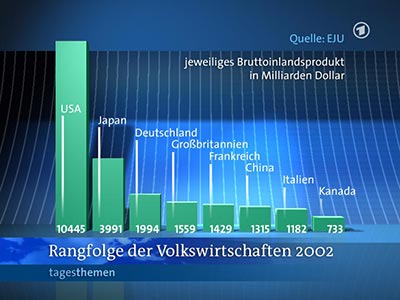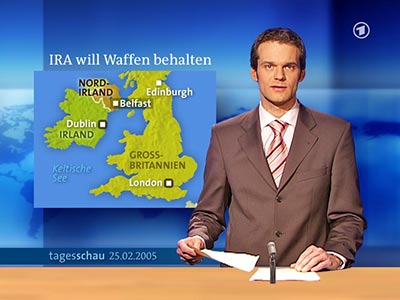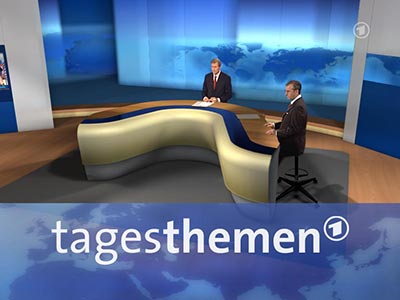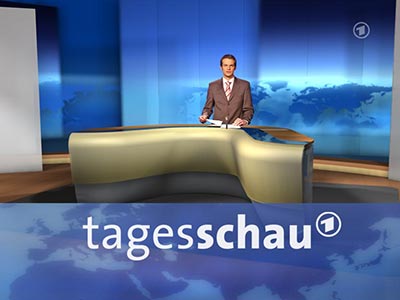
Aus der ARD-Design-HexenkücheFontShop-Beirat und Kreativdirektor der ARD-Design-Agentur DMC Markus
Hanzer hat uns Bilder aus der Entwurfsphase des
Tagesschau/Tagesthemen-Redesigns geschickt. Hanzer kämpft seit 4 Jahren
für die Erneuerung der Nachrichtensendungen. »Du kannst Dir nicht
vorstellen, wie unglaublich mühsam dieser Prozess ist« schrieb er uns
heute. Seiner Mail lagen 4 Abbildungen bei, die im Februar 2005 den neuen Weg
wiesen
...
![]() Markus Hanzer über die Rolle des Designs in News-Sendungen:
»Nachrichtenprogramme leben vom Vertrauen, von der Glaubwürdigkeit und
von der Aufmerksamkeit die ihnen geschenkt wird. Im Vordergrund steht deshalb
der ungetrübte Blick auf die Ereignisse des Tages. Dort jedoch, wo Fakten
sich nicht unmittelbar im Bild festhalten lassen, muss Design diese sichtbar
machen.«
![]() Tagesschau-Intro in der Entwurfsphase: ruhiger Hintergrund, Modell eines Nachrichtentischs, stehende Moderation Hanzer über die Bedeutung der Schrift für das Corporate Design eines TV-Senders: »Typografie ist auch im Bereich bewegter Bilder ein leistungsfähiges Instrument, um die Marke des Absenders sichtbar zu machen und über die vermittelten Inhalte hinaus von der eigenen Grundhaltung zu erzählen.« ![]() Tagesthemen-Intro in der Entwurfsphase: Doppelmoderation, Stehhilfe, U-förmiger Nachrichtentisch Hanzer über die Vorzüge der Schriftsippe Thesis: »Mit Hilfe der Thesis und der auf dem gleichen Formenkanon aufbauenden TheAntiqua B von Lucas de Groot steht ARD aktuell eine Schriftfamilie zur Verfügung, die allen Anforderungen einer modernen Berichterstattung gerecht wird.« ![]() Schwebende Hintergrundgrafik (Schrift TheSans), weiße Schlagzeile (TheAntiqua), vertrautes ARD-Blau Hanzer über die verbesserte typografische Darstellung: »Aktuelle Produktions- und Übertragungstechnik sowie eine deutliche Verbesserung bei der Bildqualität der Endgeräte erlauben heute einen differenzierten Umgang mit Schrift auf dem Bildschirm.« ![]() Aufwändige Säulengrafik wie in einer Tageszeitung: TheAntiqua-Headline, TheSans-Beschriftung, Proportionalziffern Das von Markus Hanzer mit der Agentur DMC für ARD aktuell entwickelte Design knüpft bewusst wieder an die hoch entwickelte Tradition der Zeitschriftentypografie an und nutzt die unterschiedlichen Schriftschnitte um verschiedene Informationsebenen voneinander unterscheidbar zu machen: Headline, Bildunterschrift, Erklärungen, Zusatzinformationen u. v. m. Herausgegeben: Di - Juni 21, 2005 at 11:35 vorm. | |